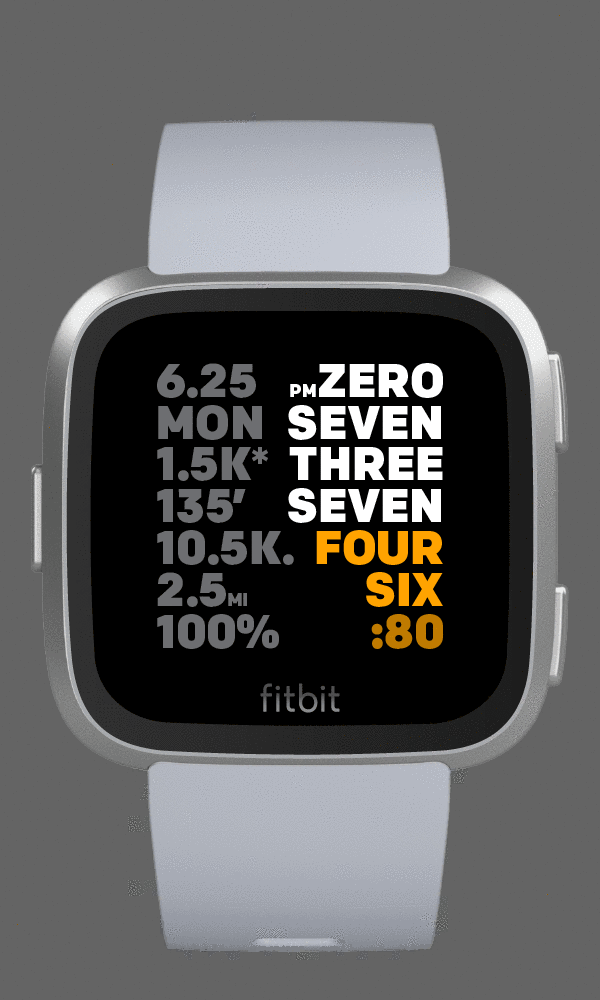
Suche Font der TTMM Fitbit Clock Faces (ähnlich DIN)
ich suche die Schriftart der TTMM Fitbit Clock Faces.
Ich kann ähnliche Fonts finden, aber nicht ganz genau diese. Sie ähnelt etwas der DIN Schrift, aber man achte auf die 6 und 3
Weiß jemand, wie diese Schriftart heißt? Es wäre toll, wenn mir jemand weiterhelfen könnte! :)
Die Colfax ist es.
Ich hab auch nur schnell™ danach gesucht … ;-) "fitbit clock font" bei Google eingegeben, der erste Treffer ist der oben verlinkte Styleguide, dort ist die Colfax genannt. :gimmifive:
Und dort sind auch die anderen bei fitbit verwendeten Schriftarten genannt.
Auf diese, an sich naheliegende, Idee bin ich gar nicht gekommen, weil die watch faces von einem unabhängigen Designer sind. Dass er einen Standard Fitbit Font benutzt, kam mir nicht in den Sinn.
fitbit ist da wohl sehr restriktiv, wie man dem Guide entnehmen kann. Ist aber an sich eine tolle Sache, weil die Dinger ja weltweit mit unterschiedlichen Schriftsystemen zum Einsatz kommen. Wusste ich vorher auch nicht.
Ich mag die Colfax ganz gern und habe sie auch bei den Impact-Alternativen aufgenommen, daher kam sie mir sofort in den Sinn.
Ich dachte aber tatsächlich, dass es eine abgewandelte Form der Colfax wäre, da bei solchen OS-UI-Fonts eigentlich eher Exklusiv-Schriften bzw. eigens dafür entwickelte die Regel sind. Von daher war der nachgereichte Link von @bertel nochmal interessant und bereichernd. 🙂
Ja, sie ist sehr geradlinig und elegant, besonders zBsp die "5". Als ich sie bei der Suche mit den auf diversen Webseiten angebotenen, auf den ersten Blick ähnlichen Schriftarten verglichen habe, wurde mir das erst richtig klar.